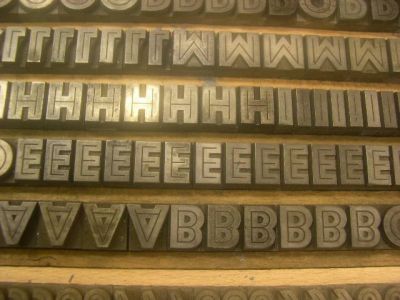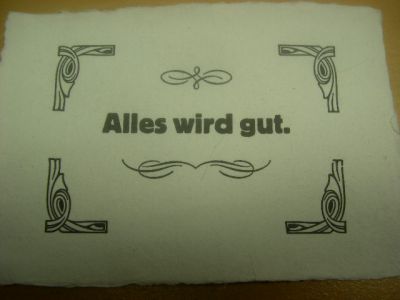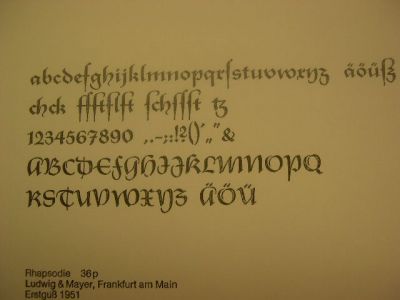
Fraktur – aber wo?
Vielerorts und auch in diesem Forum wird häufig behauptet, dass gebrochene Schriften wieder im Trend lägen und auch öfters wieder eingesetzt würden. Dass viele gebrochene Schriften eine Wieder-Entdeckung verdienten, versteht sich von selbst – aber wo sind denn die Beispiele für deren Verwendung? Abgesehen von punktuellen Experimenten einzelner Typographen sehe ich im Alltag kaum gebrochene Schriften in größerem Einsatz.
Kann mir jemand Hinweise geben, wo Fraktur z. B. in neuen Buchpublikationen gezielt eingesetzt wurde (und nicht wieder das Bsp. von Brinkmann/Boses Derrida-Ausgabe…). Ich mag gebrochene Schriften grundsätzlich sehr – aber für die behauptete ‹Renaissance› fehlen mir die Belege…
Die „Renaissance“ betrifft eher den Stylo-Trendy-Bereich. Auf T-Shirts, Trucker-Baseballcaps, Büchern, Plattencovern etc. steht die (oft geschredderte) Fraktur skurrilerweise für Punk, Rebellentum und sinnfreien Zeitgeist.
Danke für die Beispiele – in der Werbung und im Trendbereich hat sich die Fraktur offenbar ja tatsächlich von den deutschnationalen Assoziationen befreit und kann ohne schlechtes Gewissen auch für anderes (Buchcover «Markt und Rebel» – merkwürdig) eingesetzt werden. Solche Beispiele gibt es ja zuhauf. Ich meinte eher den Einsatz als Textschrift, der, so wurde es in einer Zeitschrift aus dem Verlagsgewerbe behauptet, wieder ‹im Kommen› sei – wobei ich gerne einmal den Beweis sehen möchte.
Der würde mich allerdings auch interessieren.
Ich halte es allerdings für ein Gerücht, denn die Lesegewohnheiten haben sich irreversibel von der Fraktur wegbewegt.
apropos (ich hoffe richtig geschrieben) lesegewohnheiten:
ich wäre ja mal gespannt, wenn ein italic-schnitt mal als brotschrift verwendet wird.
Früher war das ja gang und gebe. eine italic imitiert ja mehr oder weniger eine
handgeschriebene schreibschrift und lesbar sind diese schnitte auch.
ist halt alles eine gewöhnungssache.
Ich meinte eher den Einsatz als Textschrift, der, so wurde es in einer Zeitschrift aus dem Verlagsgewerbe behauptet, wieder ‹im Kommen› sei – wobei ich gerne einmal den Beweis sehen möchte.
Frag’ doch vielleicht am besten die Redaktion der Zeitschrift und poste die Antwort hier ins Forum! Es besteht ja Interesse!
Na ja, auf alle Fälle wird im Bereich Westcoast-/ Gansta-Rap (für die Hip Hop-Ignoranten: das ist Rap-Musik von der Westküste der USA) die Fraktur gern und häufig eingesetzt. Aber das bereits seit mehr als zwanzig Jahren ...
Bei mir liegt noch eine Ausgabe des britischen Magazins sleazenation aus dem Jahr 2000 (Februar) herum.
Hier wurden die Head- und Subheadlines in (einer) Fraktur gesetzt.
... Ich meinte eher den Einsatz als Textschrift, der, so wurde es in einer Zeitschrift aus dem Verlagsgewerbe behauptet, ...
Ist mir auch nichts bekannt. Solange ein Verlag eine gut lesbare Fraktur nicht auch für längere Texte einsetzt, wird sich daran wohl leider auch nichts ändern. Beispiele hätten ja eine Geheimsprache bei Harry Potter sein können, oder die Traumsequenzen bei Endes Momo, was ja auch angedacht gewesen war. Oder längere Texte in einer Rotunda bei Illuminati, wo ja eine Gotisch für das Siegel verwendet wurde. Leider nicht umgesetzt.
Im Buch Der Sonnenwirt von Hermann Kurz, Jürgen Schweier Verlag 1980, 3. Auflage Mai 2002 ist auf dem Vorsatz auf zwei Seiten der „Württ. Fahndungsbrief von 1758 gegen Friedrich Schwan“ in einer Fraktur (Ähnlichkeiten zur Walbaum, aber nicht ganz) nachgedruckt. Der Titel des Buches ist auch in Fraktur. Nichts zeitgenössisches, aber immerhin. Die Originalausgabe von Hermann Kurz ist vom November 1854, vordatiert auf 1855.
Die Geschichte dieser Person hat übrigens Friedrich Schiller zu „Die Räuber“ (1781) und der Erzählung „Verbrecher aus verlorener Ehre“ inspiriert.
Zwei Beispiele für die Verwendung von Fraktur kann ich beisteuern.
Eines habe ich gerade beim Durchblättern von »Lesetypographie« gefunden. Dort ist auf Seite 63 eine Doppelseite aus »Jacques Derida, meine chancen, 2000« abgebildet. Dieses Heft ist überwiegend in einer Schwabacher gesetzt.
Das zweite Beispiel ist der Science-Fiction-Roman »Der Untergang der Stadt Passau« von Carl Amery, 1976. Dort sind ca. 10 Prozent des Textes in Fraktur. Die Textstellen Auszüge aus einer fiktiven handschriftlichen Chronik dar.
Nur falls man das Heft (49 S.) „Meine Chancen“ sucht: Jaques Derrida schreibt man mit zwei r :)
Vielen Dank für die Beispiele!
Jaques Derrida schreibt man mit zwei r :)
… und Jacques mit c :-)
Eines habe ich gerade beim Durchblättern von »Lesetypographie« gefunden. Dort ist auf Seite 63 eine Doppelseite aus »Jacques Derida, meine chancen, 2000« abgebildet.
Ich hatte ursprünglich geschrieben: «Kann mir jemand Hinweise geben, wo Fraktur z. B. in neuen Buchpublikationen gezielt eingesetzt wurde (und nicht wieder das Bsp. von Brinkmann/Boses Derrida-Ausgabe…).» :)
>Die Lichte Fette Grotesk gefällt mir hervorragend. Die empfinde ich sogar tatsächlich als "preußisch" - nicht im korrekten historischen Sinn, aber als Adjektiv
Hmmm, was hat die Lichte Fette Grotesk mit "preußisch" zu tun - verstehe nur Bahnhof. Kläre mich mal auf, was du unter diesem "mythischen Preußen" verstehst, hinsichtlich Schriften und deren Gestaltung. Ich denke das würde uns ein paar "politische" Diskussionen ersparen...
die Lichte Fette Grotesk ist in der Mitte ausgespart, interessant... gibt es diese auch schon im Andruck?